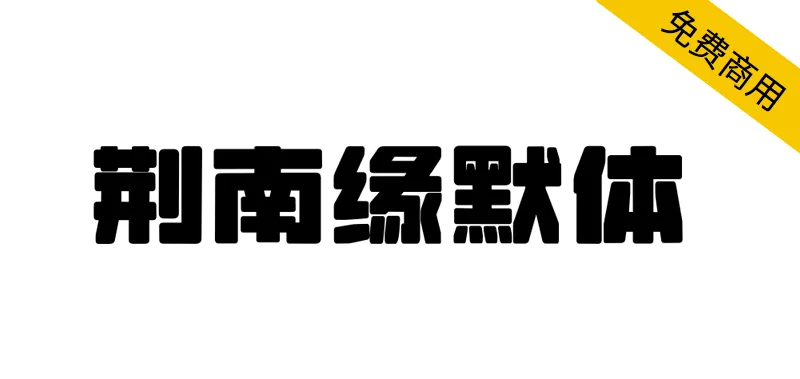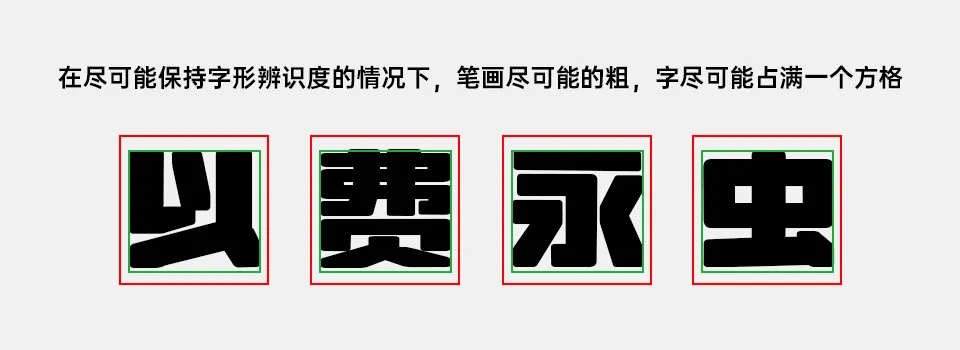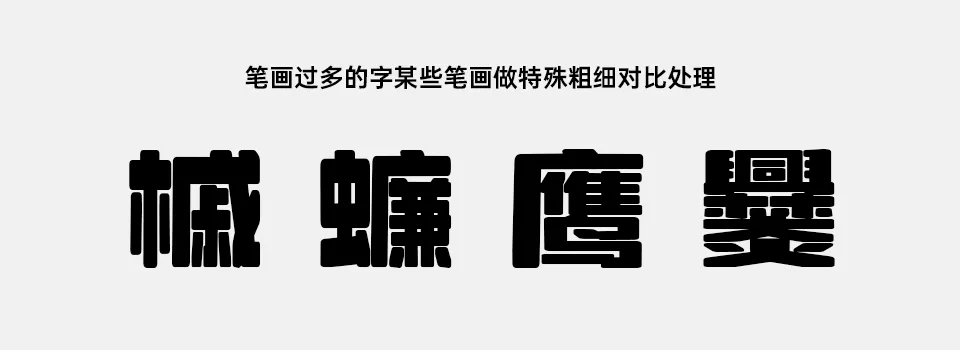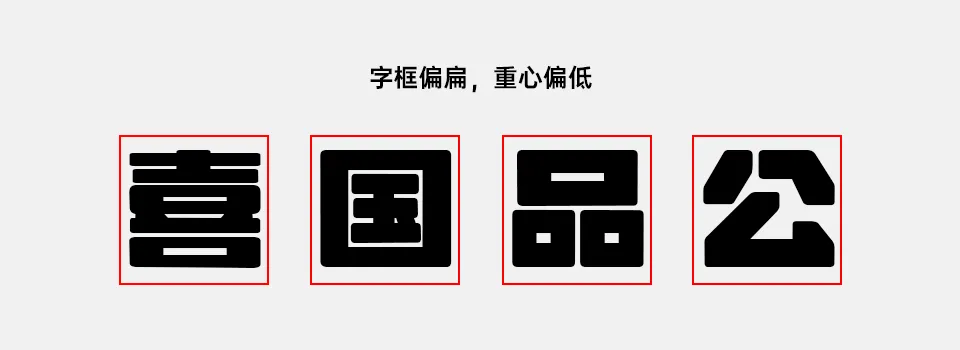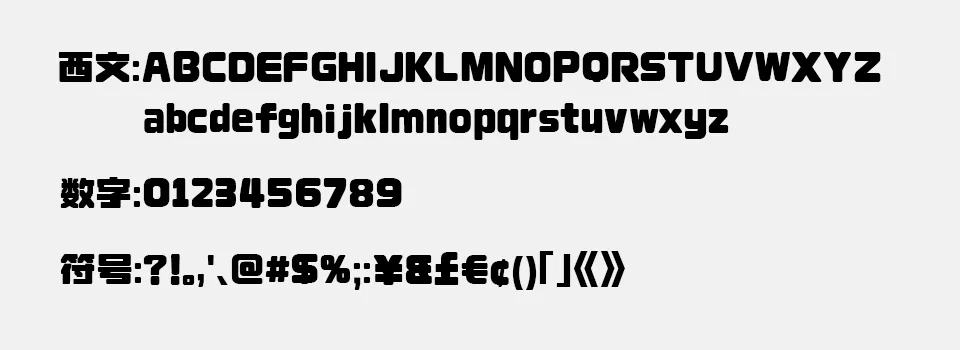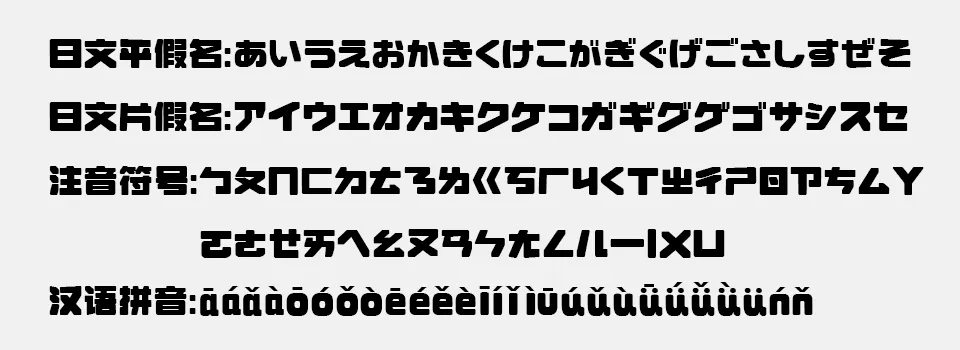
2020年突如其來的疫情,讓我想創作一套屬於自己的字體的願望從遙不可及的理想變成了觸手可及的現實。總想著這套字體一定要是在大街上隨處可以見到的那種風格。甚麼樣的字體最受歡迎?經過我個人的仔細觀察,發現還是粗的類綜藝黑體的美術字最受歡迎,這類字體總能在第一時間抓住人的眼球。於是我就按照自己的想法繪製了一種儘可能佔滿一個偏扁的長方形的粗黑字,沒想到從去年年初到現在一年多的時間居然還把將近7000字的完整版做完了。
一開始的字體風格還不想現在這樣,圓角是後來逐漸加上去的,我想要一種增加字體趣味性但是又不要看起來很像疊圓體之類的圓體美術體,於是就形成了如今的圓角。
理想的設計用途:該字體非常適合店招、房地產廣告、地鐵公交站廣告海報、線上及線下的各類產品宣傳、個人VLOG封面標題字體等。
在儘可能保持字形辨識度的情況下,筆畫儘可能的粗,字儘可能佔滿一個方格
筆畫過多的字某些筆畫做特殊粗細對比處理
字框偏扁,重心偏低
包含了西文、數字、符號、日文平假名、日文片假名、注音符號、漢語拼音等